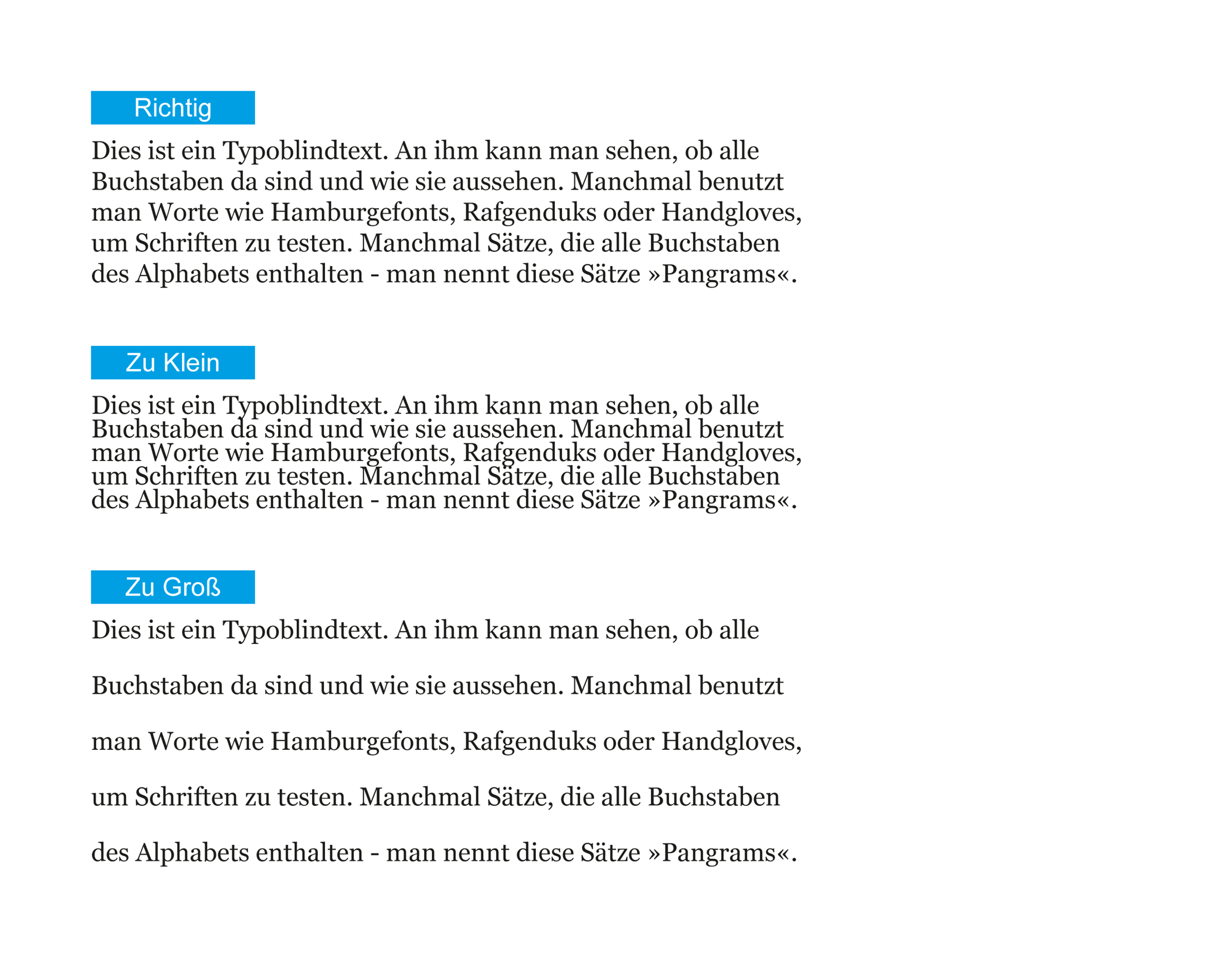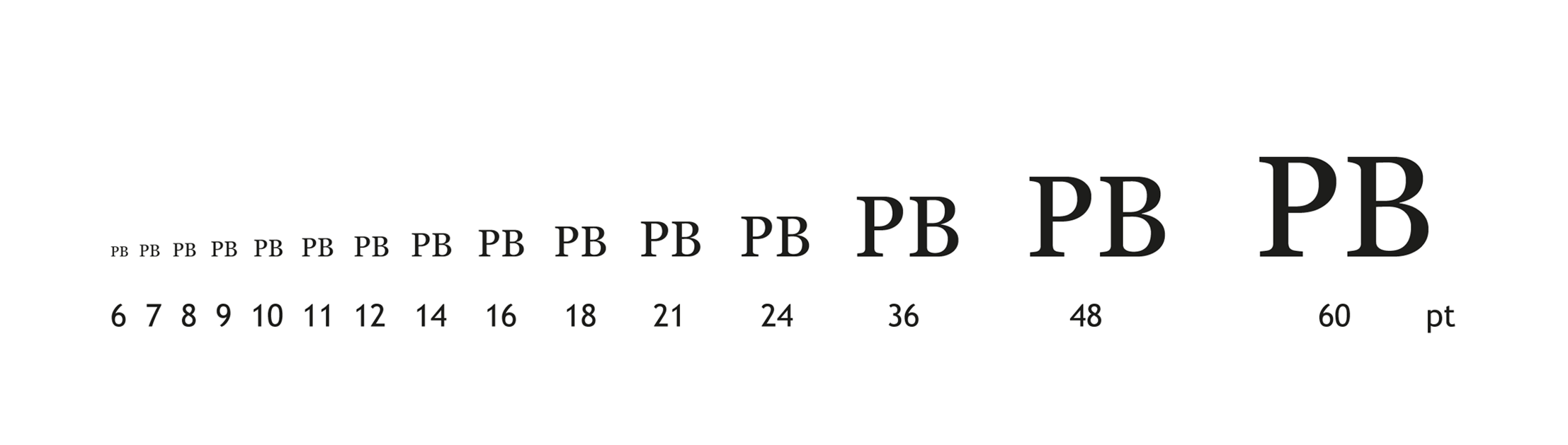
8 Regeln für eine bessere Typografie
Ein kurzer Überblick zur Typografie
Was ist Typografie? Der Begriff kommt aus dem Altgriechischen und setzt sich zusammen aus dem Wort „Typos“ für „geprägt“ oder „Form“ und dem Begriff „Graphein“ für „schreiben“, am besten übersetzt durch „Arbeiten mit Schrift“. Im Ursprünglichen Sinne bezieht sich die Typografie auf sämtliche Bereiche der „Bucherdruckerkunst“, vom Druckschriftenentwurf über den Letterguss und die Methoden zur drucktechnischen Schriftvervielfältigung bis hin zur formalen Gestaltung von Druckwerken. Dem rasanten technischen und gesellschaftlichen Strukturwandel geschuldet, lässt sich der Begriff Typografie heutzutage nicht mehr klar und allgemein gültig definieren. Typografie steht einerseits für die gedruckte Schrift, bezeichnet jedoch auch den Gestaltungsprozess von Druckwerken und elektronischen Medien mittels Bild, Schrift, Linien, Flächen und typografischem Raum. Der weitgefächerte Begriff Typografie umfasst also nicht nur die Gestaltung eines Layouts und den Entwurf und das Design von Schriften. Festhalten lässt sich jedoch, dass die Kunst des Typografen darin besteht, Gestaltungsmerkmale in geeigneter Weise zu kombinieren.
Jan Tschichold
Einer der einflussreichsten Typografen des 20. Jahrhunderts
Es folgen nun die Tipps für eine stimmige Typografie.
#1 Die Zeilenlänge des Fließtextes
Die Zeilenlänge beeinflußt den Lesefluss eines Textes. Ist die Länge einer Zeile zu lang oder zu kurz, empfindet der Leser den Text als ermüdend oder störend. Eine lange Zeile unterbricht den Lesefluss, da das Auge des Lesers den Beginn einer neuen Zeile erst suchen muss. Die optimale Anzahl der Zeichen der Buchstaben ist von Text zu Text unterschiedlich, empfohlen werden 50-80 Zeichen einschließlich der Leerzeichen.
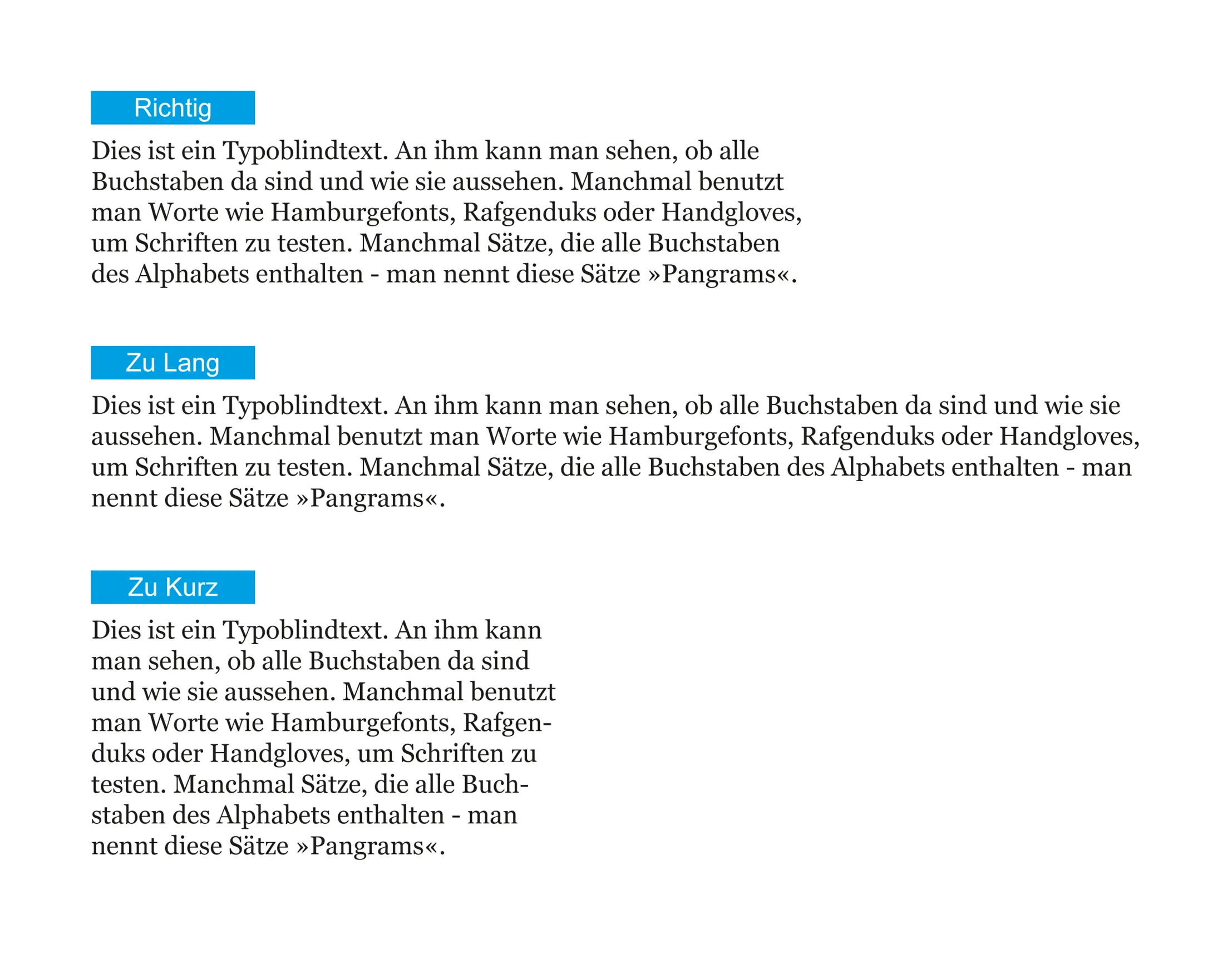
#2 Der Zeilenabstand beim Fließtext
Der Zeilenabstand spielt eine große Rolle für die Lesbarkeit eines Textes. Ist dieser korrekt gewählt, ist es für den Leser einfacher dem Text zu folgen und das Erscheinungsbild des gesamten Textes wird verbessert. Viele Faktoren haben Einfluß auf den Zeilenabstand: Schriftart, Schriftgröße oder Zeichenbreite. Je länger eine Zeile desto mehr Zeilenabstand wird benötigt, je kürzer desto weniger.
#3 Optischer Randausgleich bei Anführungszeichen
Anführungszeichen sollten immer außerhalb des Textes eingefügt werden. Stehen Sie innerhalb eines Textblocks unterbricht dies den Lesefluss des Lesers. Für diese und andere Sonderzeichen steht beispielsweise in InDesign die Funktion des optischen Randausgleichs zur Verfügung.
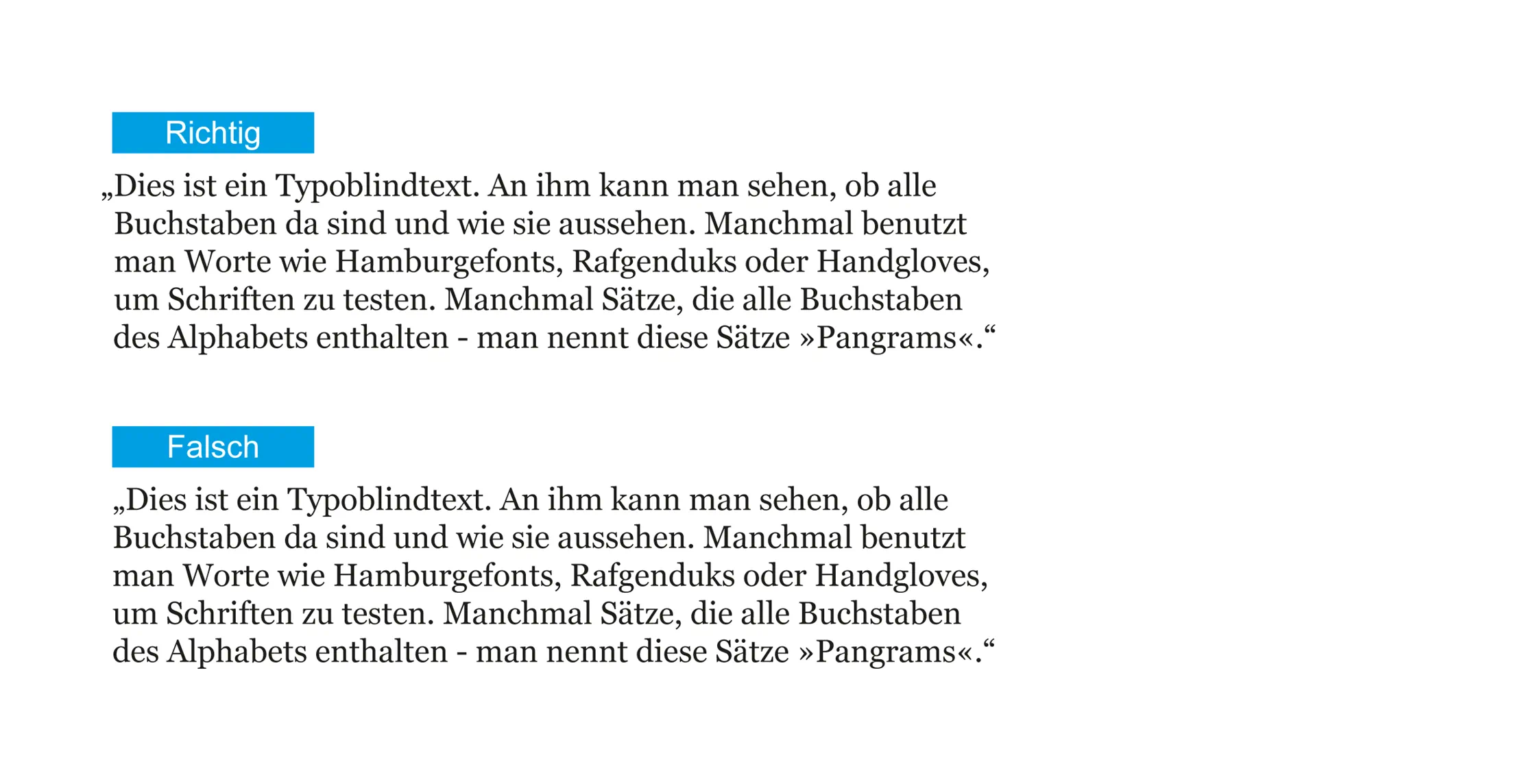
#4 Vertikale Ausrichtung des Textes im Layout
Das Einhalten der Schreiblinien ist die Grundlage für den Lesefluss eines Textes. So ist der Leser fähig, diesem einfach und schnell zu folgen, unabhängig von der verwendeten Schriftart, Schriftgröße oder Zeilenabstand.
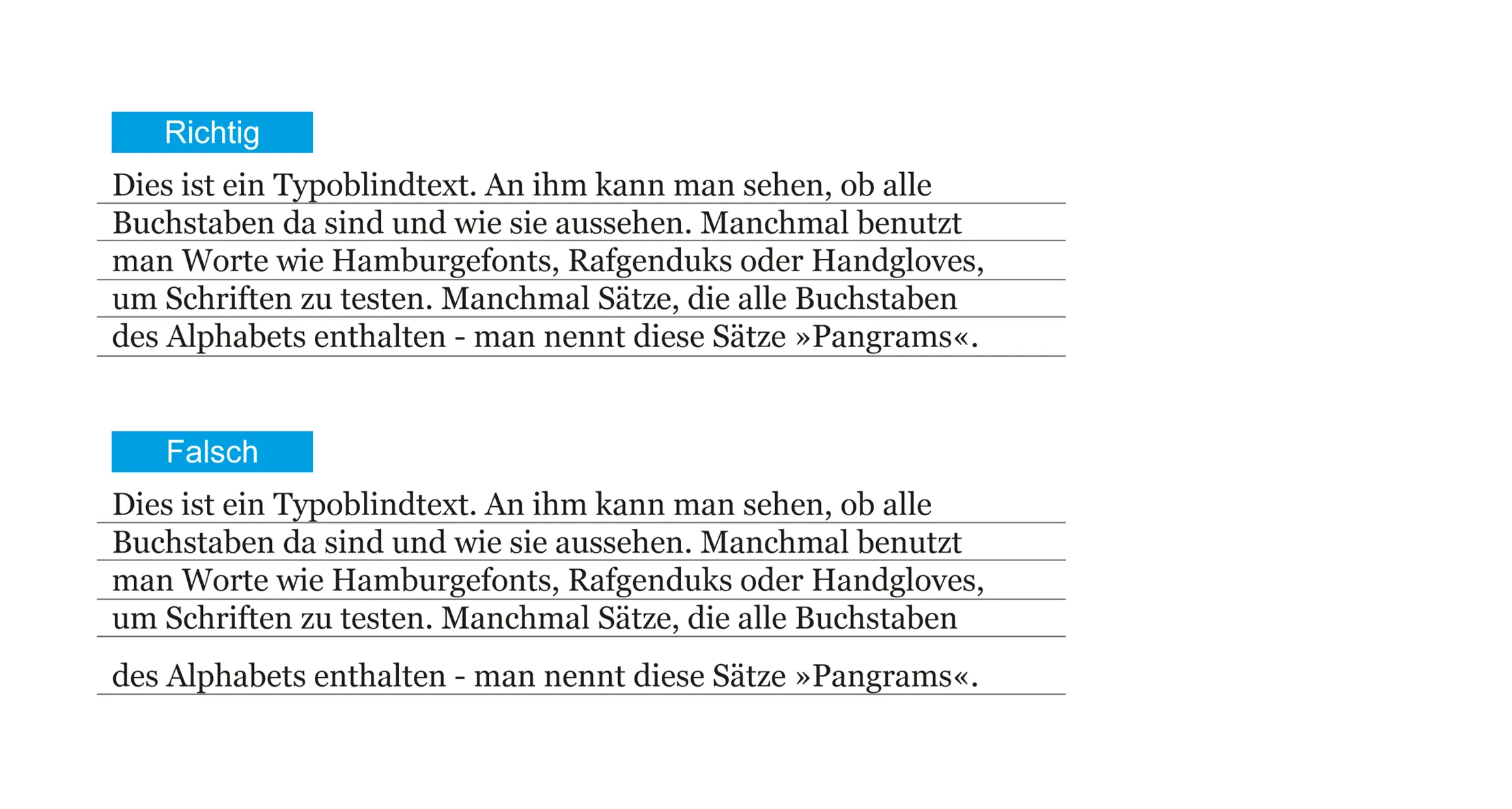
#5 Das Hurenkind und Schusterjunge
Als Hurenkind bezeichnet man einen Satzfehler, bei dem die letzte Zeile eines Absatzes eine neue Spalte oder Seite eröffnet. Ein Schusterjunge ist ein Satzfehler, bei dem die erste Zeile eines Absatzes die letzte Zeile einer Spalte oder Seite bildet. Hurenkinder und Schusterjungen reißen Löcher in eine Textseite und beeinflussen die Lesbarkeit in hohem Maße. Sie können durch anpassen der Schriftgröße, Zeilenlänge, Zeilenabstand und Vertikale Ausrichtung vermieden werden. Ich möchte euch an dieser Stelle auch meinen Printblogger-Artikel zum Schusterjungen und Hurenkind ans Herz legen.
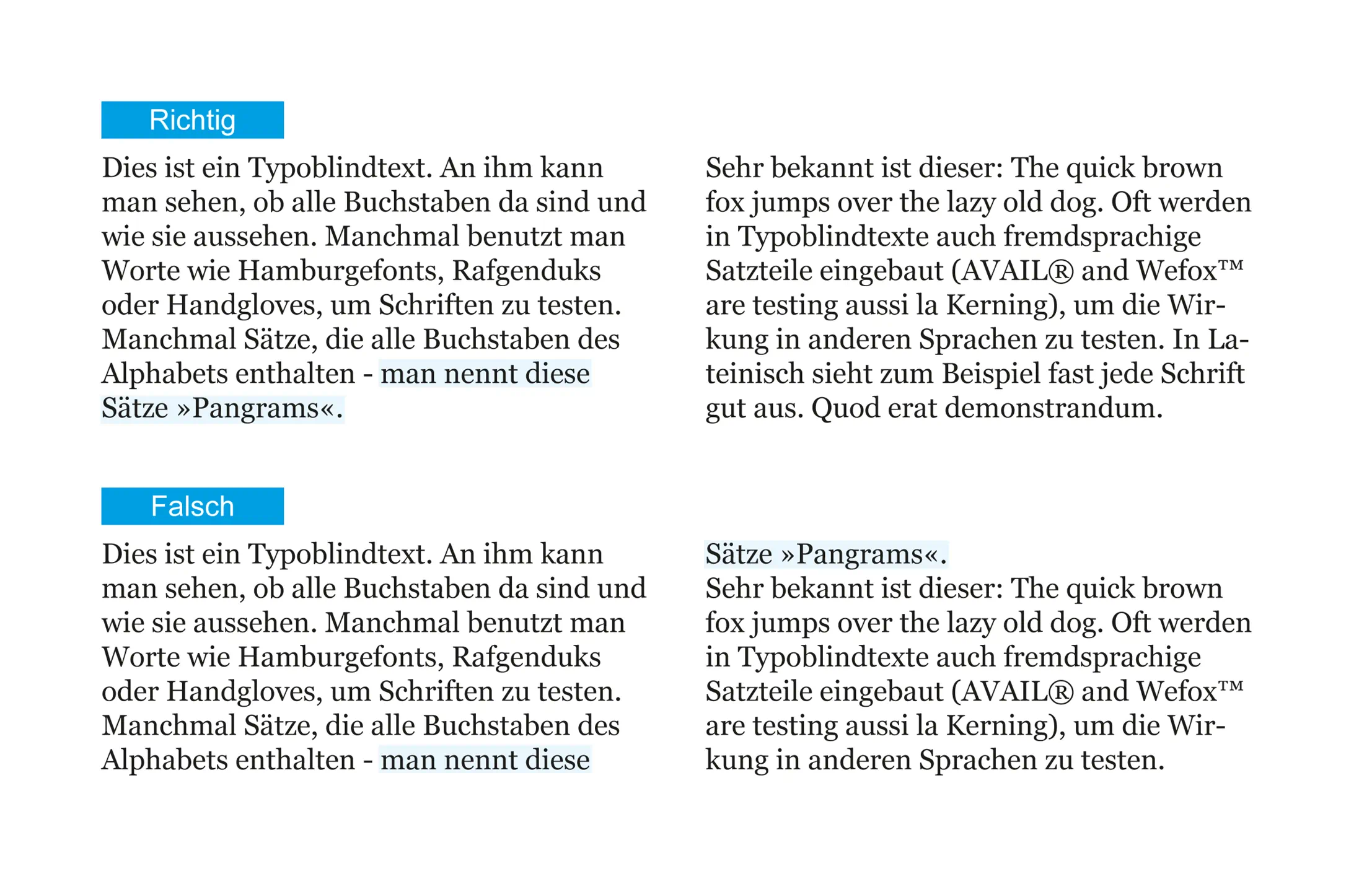
#6 Hervorheben der Schrift im Layout
Es ist wichtig, ein Wort hervorzuheben ohne des Lesefluss zu unterbrechen. Möglichkeiten dazu existieren viele; Fettgedruckt, Hoch- Tiefgestellt oder Unterstreichen. Die angenehmste Art ist, ein Wort Kursiv hervorzuheben. Wofür ihr euch auch immer entscheiden, vermeidet es, die einzelnen Formen zu vemischen.
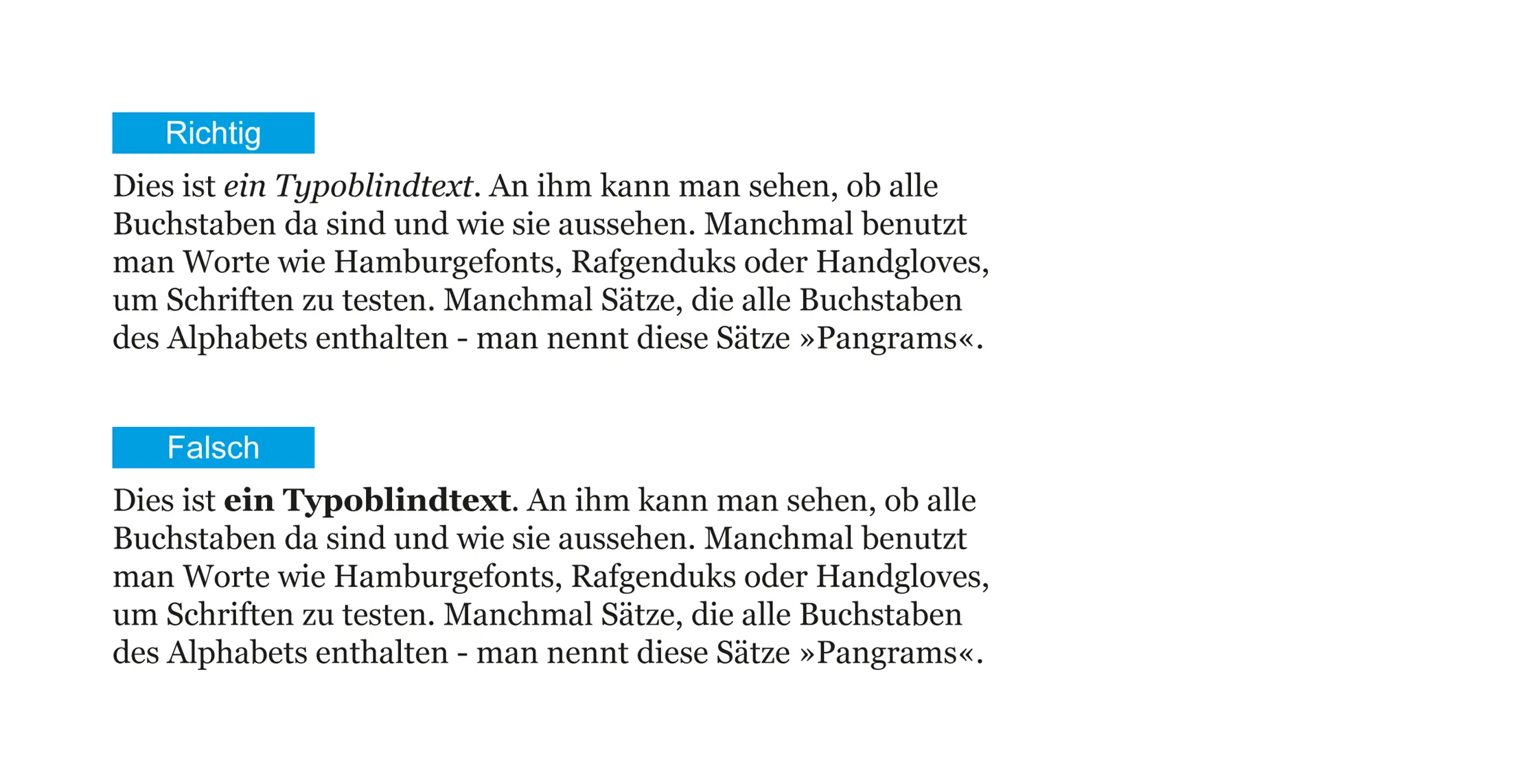
#7 Der Flattersatz bei Schrift
Der Flattersatz bezeichnet in der Typografie eine Satzform, bei der die Zeilen ungleichmäßig auslaufen. Stellt bitte sicher, dass die nicht ausgerichtete Textseite gleichmäßig und ohne tiefe Löcher gehalten ist.
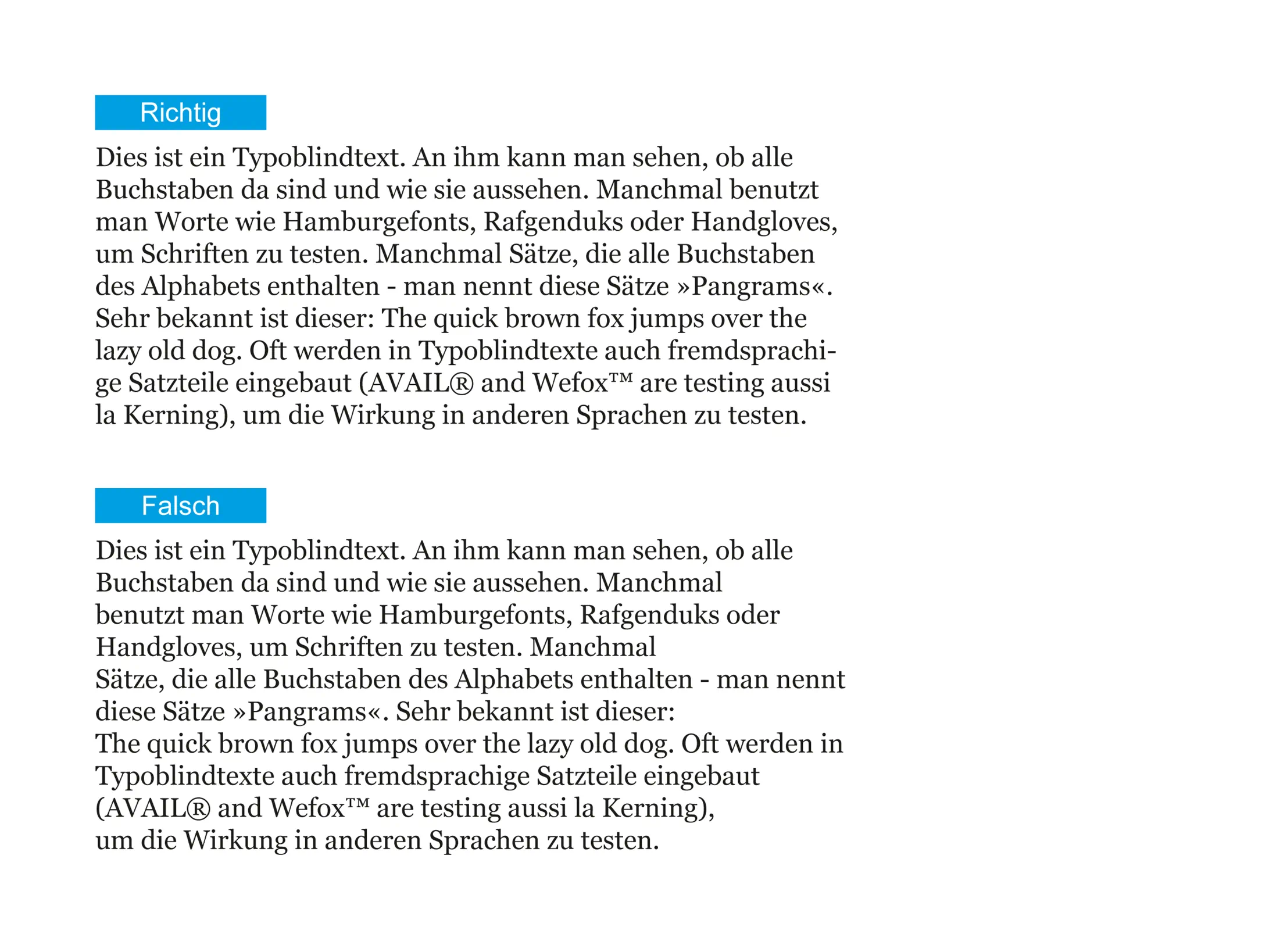
#8 Die Skalierung der Buchstaben (Schriftgröße)
Arbeitet zusätzlich immer mit einer definierten Skala an verschiedenen Schriftgrößen, welche im Vorfeld festgelegt wurde und an die ihr euch haltet. Die richtige Skalierung ist wichtig, da sie eine typografische Hierarchie bildet und den Zusammenhalt des Textes verstärkt. Schaut doch bei dieser Gelegenheit einmal in meine umfangreiche Sammlung stilvoller und kostenloser Fonts.